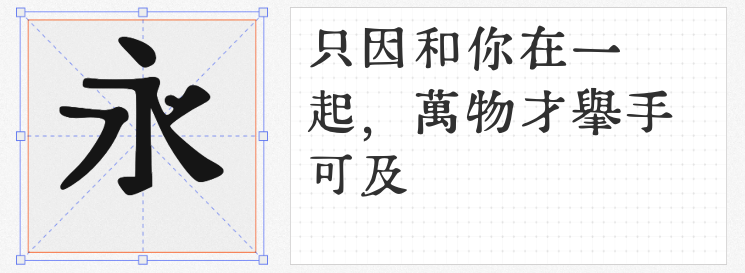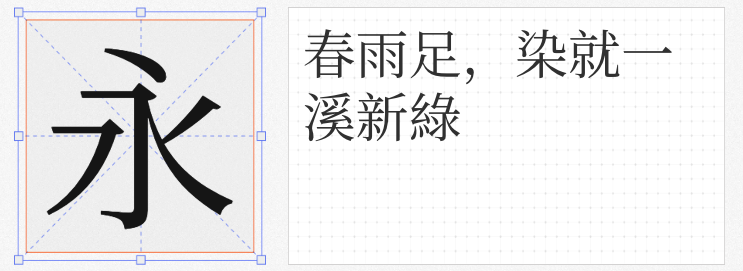
在多元设计场景中,宋体以其独特的文化底蕴与现代适配性成为设计师的“百搭利器”。本文精选四款免费可商用的宋体字体,涵盖人文温润、复古经典、像素美学与古籍规范四大风格,助力品牌视觉与创意表达突破边界。
作为开源字体项目,香萃等粗宋以“平滑柔和”的笔画起收与转角设计打破传统宋体的机械感,中宫略紧的结构赋予其“舒适感与严肃性并存”的独特气质。通过重新设定横竖比例与局部改良,字体在屏幕显示中呈现清朗温润的视觉效果,同时适配印刷媒介。其涵盖泛中日韩超20000字符,除“浅残践劲”等特定汉字采用中国大陆规范字形外,其余均保留旧字形,为古籍修复、文化出版等场景提供历史韵味。基于SIL Open Font License 1.1协议开源,设计师可自由修改与传播,但需遵守禁止单独售卖字体文件的规定。
由设计师daredemotypo复刻自日本秀英舍活版制造所1913年《明朝五号活字摘要録》的ICHIGAYA明朝体,通过InkScape自动追踪技术将百年活字转化为数字字体,保留了“刀刻纹理”与“墨韵渗透”的复古质感。字体严格遵循《活字注文用当用漢字表》规范,适用于广告设计、文化展览等场景,传递东方美学的历史厚重感。尽管采用作者声明授权,但明确允许个人与企业免费商用,仅需规避违法用途。
针对《古籍印刷通用字规范》的实践断层,汇文系列作者特里王以思源宋体为框架,融入文津宋体的B区扩展字形,打造出“部件统一、结构严谨”的源古宋体。其纯古籍表版严格遵循古籍用字规范,适合学术出版、文化纪录片字幕;基于SIL协议开源的特性,使其成为古籍数字化与现代创意结合的标杆工具。
从香萃等粗宋的人文温度,到ICHIGAYA明朝体的历史回响;从纳米全大宋的像素实验,到源古宋体的古籍规范,这四款字体以不同维度诠释了宋体的现代生命力。设计师可根据项目需求自由选用,在确保版权合规的同时,为作品注入文化深度与视觉张力。